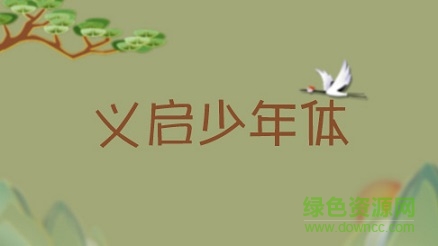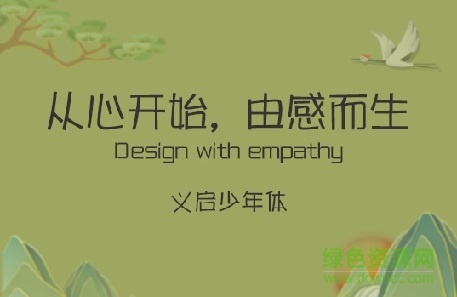
軟件介紹 軟件標(biāo)簽: 義啟 字體 義啟少年體字體是義啟字體庫中一款常用簡體字體,綠色資源網(wǎng)帶來的為ttf直裝字體,安裝很方便。正如它的名字一樣,整個效果給人感覺非常具有活力,像充滿活力的少年樣,設(shè)計朋友們的最愛字體類型。趕快收藏起來吧!義啟少年體安裝說明方法一:控制面板/字體/文件/安裝新字體;方法二:直接將字體復(fù)制到C:\WINDOWS\Fonts。方法三:針對win7系統(tǒng),用戶只需選中字體右鍵安裝即可。使用說明本站所有字體資源僅供個人學(xué)習(xí)與參考,如需商業(yè)使用請到相關(guān)官網(wǎng)授權(quán)。 軟件截圖 上一張下一張(1 / 1) 安裝詳細(xì)截圖 猜你喜歡 義啟字體 義啟字體 義啟字體是義啟家族(17font)推出的一系列字體合集,包括了很多類型,如:義啟粗楷體ttf、義啟萌妹體、義啟明星字體等,每款字體都很有特點,當(dāng)然,也很漂亮,很多朋友都喜歡使用義啟字體,趕快收藏起來吧! 查看更多>> 義啟風(fēng)尚黑字體 842KB/中文/0.0/下載 義啟星空之翼ttf 782KB/中文/10.0/下載 義啟奶萌小小喵字體 1.31M/中文/0.0/ttf版下載 義啟戀上桃花拼音字體 1.29M/中文/5.0/ttf免費版下載 義啟小南同學(xué)字體 437KB/中文/5.0/ttf免費版下載 義啟為你心動字體 592KB/中文/6.6/ttf免費版下載 其他版本下載 標(biāo)題 大小 更新日期 下載 下載地址 電腦版 義啟少年體字體 ttf版 點擊報錯 軟件無法下載或下載后無法使用,請點擊報錯,謝謝! 關(guān)閉報錯反饋 請描述您所遇到的錯誤,我們將盡快予以修正,謝謝! *必填項,請輸入內(nèi)容 本類最新 dreamweaver字體庫 首爾南山體字體 v1.06 官方版 潮字社風(fēng)云簡ttf 潮字社凌渡鯤鵬簡體字體 潮字社曾玉波手書簡字體 微博慧心字體 相關(guān)文章 Photoshop字體安裝使用方法和技巧 如何解決“無法新增字體”問題 Win 7系統(tǒng)安裝字體方法 網(wǎng)頁字體大小設(shè)置方法 怎么改網(wǎng)頁字體大小 在Linux系統(tǒng)中安裝字體的幾種方法 windows7字體顯示問題:打開某些程序的時候顯示的是亂碼 用戶評論 熱門評論 最新評論 發(fā)表評論 查看所有評論(0) 昵稱: 請不要評論無意義或臟話,我們所有評論會有人工審核. 字?jǐn)?shù): 0/500 (您的評論需要經(jīng)過審核才能顯示)